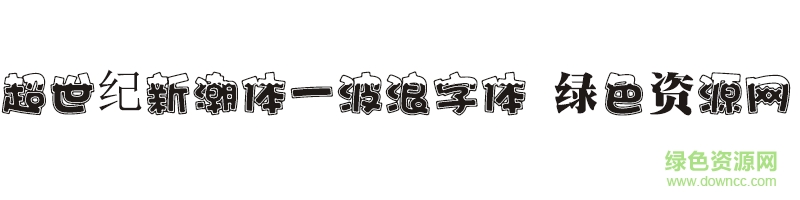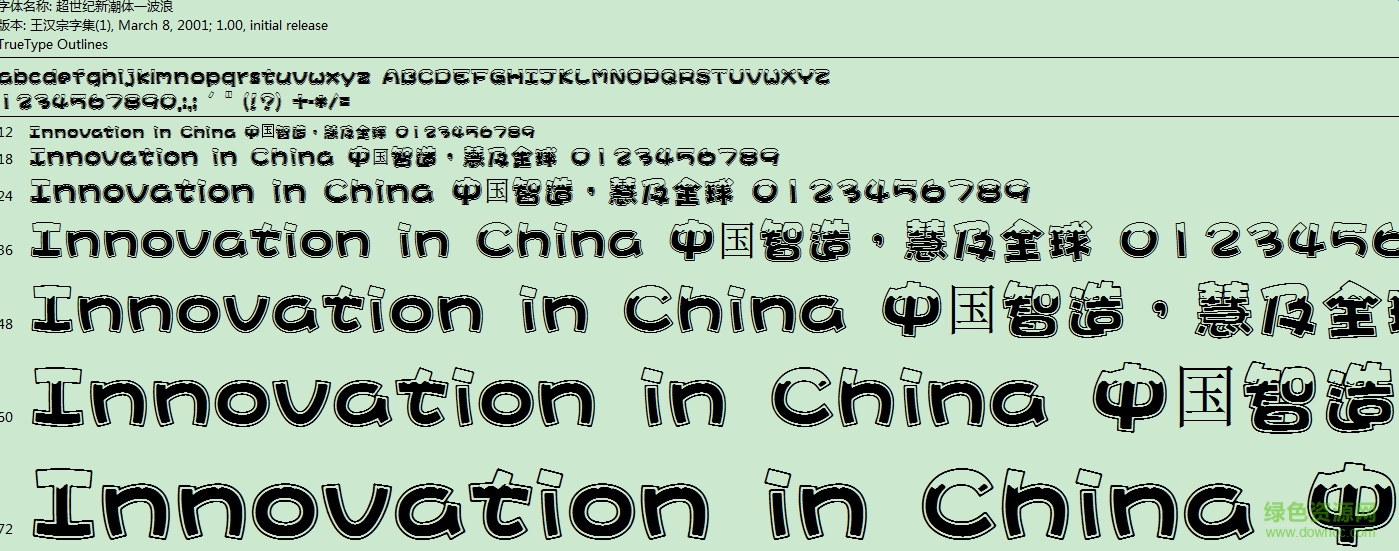
超世紀(jì)新潮體一波浪字體是一款超世紀(jì)字體系列中比較好用的字體,中空采用波浪形狀,讓字體活起來,非常適合做設(shè)計的朋友們使用,小編為大家提供免費下載地址。快來綠色資源網(wǎng)踴躍下載吧!
超世紀(jì)新潮體一波浪整體效果富有藝術(shù)性,它不支持所有字體識別,部分字體無法顯示,比較具有特色,非常適用于廣告設(shè)計中。